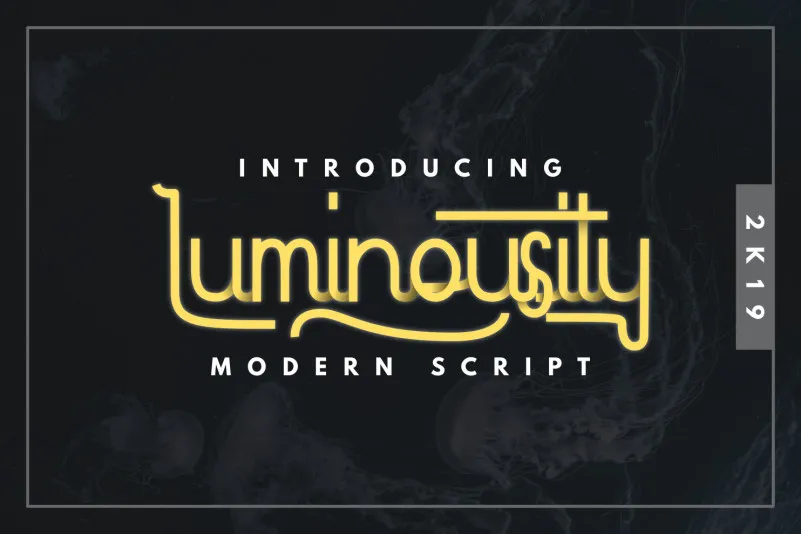
Luminousity – Modern Script Font – Download Grátis
A fonte “Luminousity – Modern Script Font” é uma opção ideal para designers que desejam trazer um toque moderno e elegante aos seus projetos, inspirada nas estilizadas postagem de papel clássicas. Desenvolvida a mão por inspirasign, esta fonte oferece tanto texto completo quanto alternativas OpenType, ligaturas comuns e até mesmo swashes adicionais para dar um toque único e personalizado. Perfeita para usos como logotipos, letras de carta, postagem, design de roupas, etiquetas e muito mais. Seu estilo moderno e delicado combina perfeitamente tanto com as criações digitais quanto com os designs tradicionais, tornando-a uma opção versátil que pode atender às necessidades do seu projeto. Esta font é um verdadeiro presente para os designers que procuram manter a essência de um estilo clássico sem perder a frescura e modernidade moderna. Com “Luminousity – Modern Script Font”, suas criações ganham uma personalidade única, tornando-a o complemento perfeito para qualquer projeto visual.